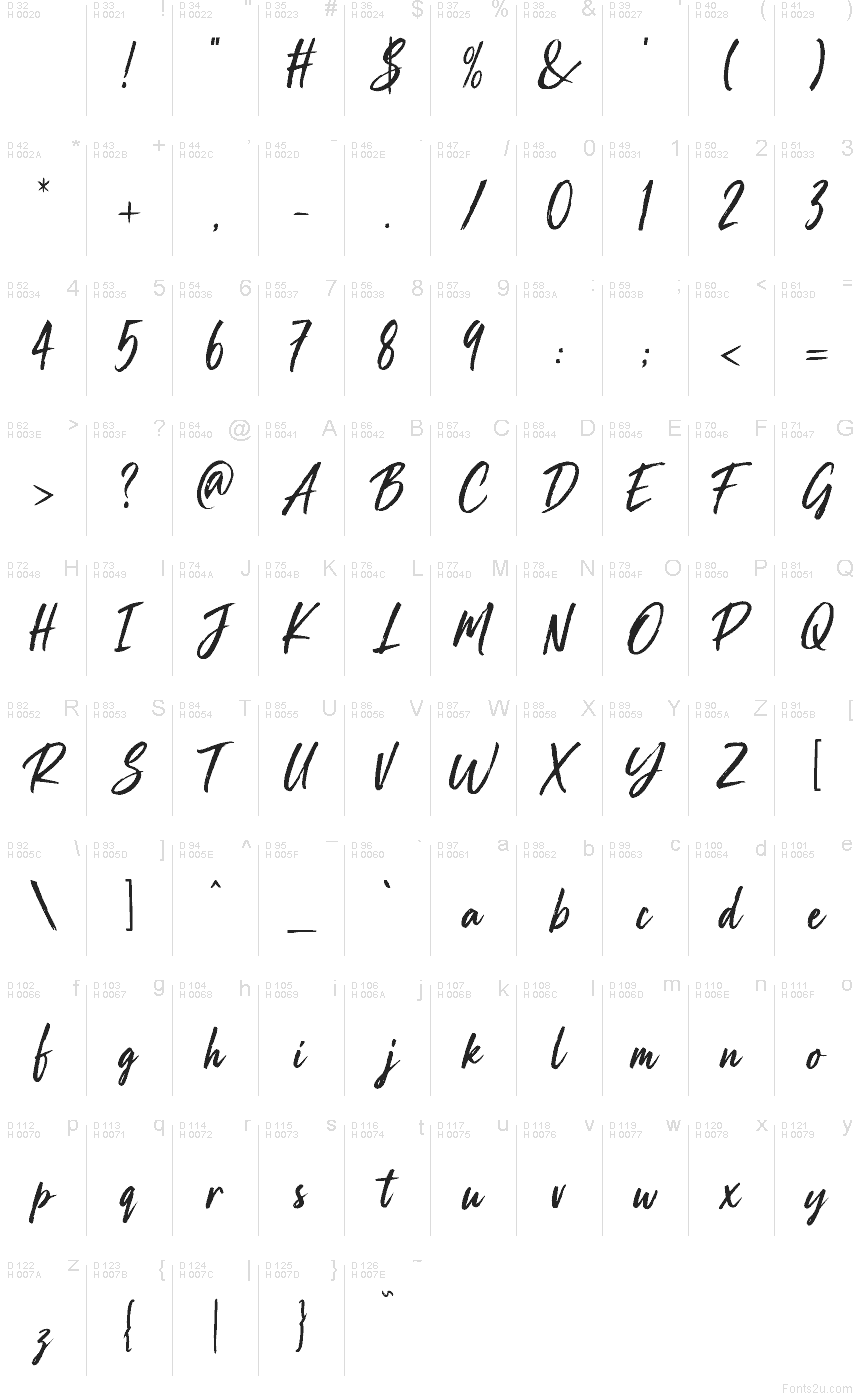
La Fabrique de Chocolats, de BlackFridayFont, es una tipografía tipo brush gratuita con el estilo desenfadado de los rótulos de café pintados a mano. Sus letras avanzan con trazos amplios y cargados de tinta, combinando curvas rápidas con remates definidos para ofrecer un diseño casual, apetecible y con un toque teatral.
Ideal para empaques de chocolate, branding de pastelerías, cubiertas de menús, titulares de carteles y publicaciones en redes sociales donde necesites ese aire de tienda tradicional. Al ser una fuente gratuita, también es una excelente opción para tarjetas de título y bocetos de logotipos. Te recomendamos usarla en textos cortos; sus pinceladas gruesas y terminaciones cortadas lucen mucho mejor cuando el tamaño es grande y llamativo.